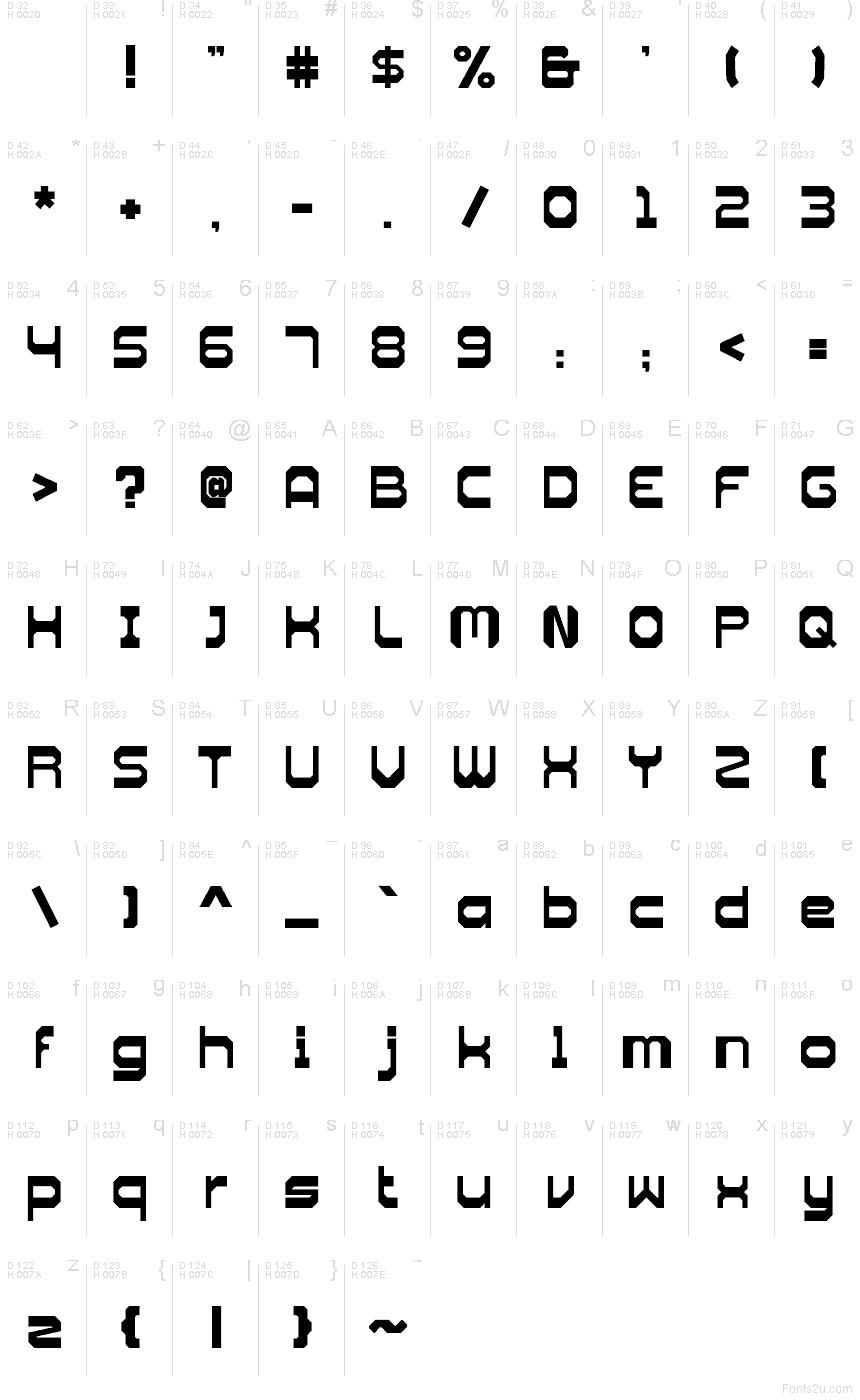
Dacosta od Tokokoo je bezplatné retro displejové písmo s neobvykle širokými, plnými literami, hlubokými zářezy a ostrým, strojově opracovaným profilem. Osekané oblouky a zkosené rohy vytvářejí osobitou, tvrdou mechanickou siluetu.
Herní studio nebo streetwearová značka by mohly tyto průrazné tvary využít pro vizuální identitu zakořeněnou v arkádové grafice a historických zobrazovacích technologiích. Plakátům elektronické hudby a sportovnímu merchandisingu vyhovují také hranaté proporce a těsně přiléhající spoje, jež evokují rychlost, strojní techniku a soutěžní podívanou. V podobě loga značky či názvu produktu proměňují opakující se úhlové řezy běžný nápis v kompaktní emblém s jasným a výrazným retrofuturistickým rázem.